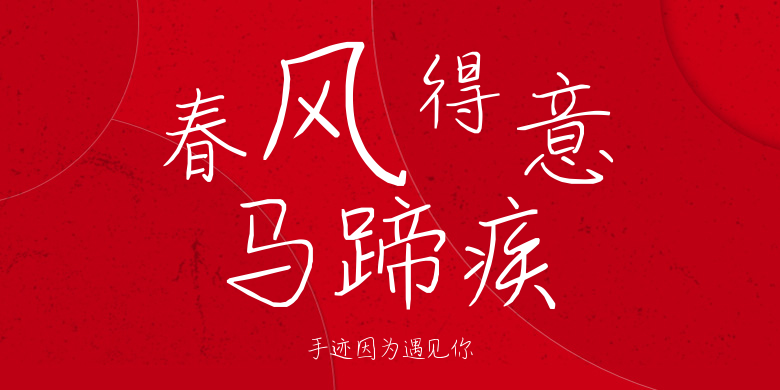
手迹因为遇见你
手迹因为遇见你,这款字体结构工整、笔画清晰,兼顾美观与易读性,适用于标题、正文、海报、包装、LOGO 等多种场景。字形优雅稳定,风格百搭耐看,适配日常排版与创意设计,让文字呈现更舒适、更具质感。手迹因为遇见你一笔一画,皆是细节,以均衡的比例、流畅的线条打造舒适视觉体验,字形端正大气,风格简约现代。无论是商业设计、品牌宣传还是日常排版,都能轻松驾驭,让文字更有格调与力量。手迹因为遇见你字体下载。